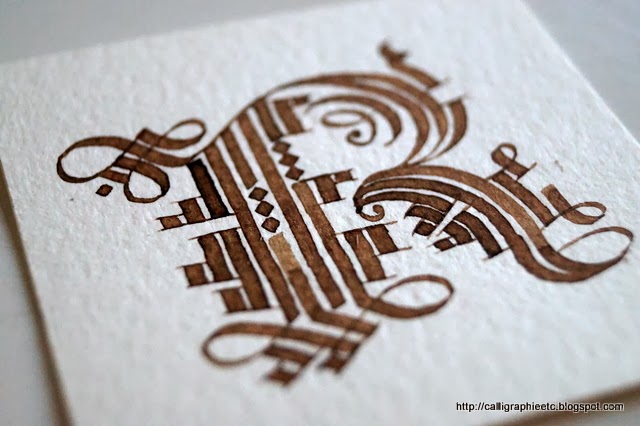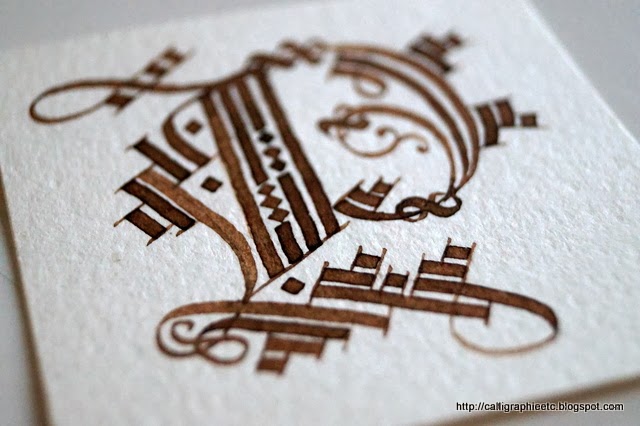
And now
the latest real letters of the second alphabet of a letter a week ... Let me
explain ... This old alphabet, like many other formerly had no "i",
not "u" or "w" ... Logic
Et comme j'ai "copié" un alphabet... même si je lui ai ajouté quelques arabesques, je n'ai donc pas écrit de "i", ni de "u", ni de "w"... Mais maintenant, ces lettres manquent quand elles n'y sont pas... A-t-on jamais vu un alphabet amputé d'un "i", d'un "u" ou d'un "w" ? ;)
And as I
have "copied" an alphabet ... even if I added him some arabesques, so
I did not write "i" or "u" or "w" ... But now,
these letters are missing when they are not there ... A Does anyone ever seen
an alphabet cut a "i", a "u" or "w"? ;)
Il a donc fallu que je les "invente" moi-même... Enfin... quand je dis "invente"... j'ai surtout "composé"... car comme je ne suis pas spécialiste de la création d'alphabet, surtout ancien, je me suis aidée des tracés de toutes les lettres pour composer les trois qui me manquaient... Donc ce n'est pas rigoureusement exact côté "historique"... Espérons juste que cela ne choque pas à côté des autres lettres...
It was
therefore necessary that I "invented" myself ... Finally ... when I
say "invented" ... I especially "compound" ... because as I
am not an expert creating alphabet, especially old, I helped plots of all the
letters to compose the three that I missed ... So this is not strictly correct
side "historic" ... Let's just hope it does not shock alongside other
letters ...
Voilà ce que cela donne...
Here's
what happens ...
Pour le "i", je voulais au départ utiliser le "j", mais cela détonnait à côté... j'ai donc utilisé le tracé vertical du "r" et du "h", puis j'ai ajouté une base comme sur le "h". Pour le haut, j'ai essayé différents motifs des autres lettres, à gauche, le haut du "j" convenait, mais à droite, ça ne me convenait pas alors j'ai inventé pour le coup.
For the
"i", I originally wanted to use the "j", but it clashed
next ... so I used the vertical layout of the "r" and "h",
then I added a base as the "h". For the top, I tried different
patterns of other letters, left, the top of the "j" appropriate, but
right, it does not suit me so I invented for once.
Pour le "u", j'ai renversé le "n", mais j'ai donné moins de "présence" à la barre verticale et davantage à la courbe. A droite, j'ai utilisé le haut du "k".
For the
"u", I flipped the "n", but I gave less
"presence" to the vertical bar and more to the curve. Right, I used
the top of the "k".
Pour le "w", j'ai inversé le "m" et utilisé un seul côté que j'ai répété puis tracé le tracé gauche du "m" inversé en miroir...
For the
"w", I reversed the "m" and used one side I repeated then
traced the route of the left "m" inverted mirror ...
Then I
added one by one, various small patterns to improve the letter ... Good ... It
looks like the kitchen or lego ... but my letters are completed ....
Anyway, now that the alphabet is finished ... and really finished ... must "really" I found a way to assemble ... ;)